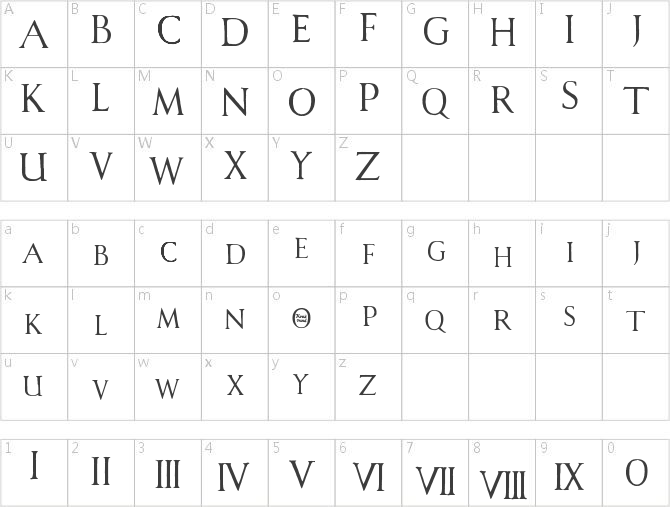
字體名稱: Antique
Antique Font by Marta van Eck
Antique Font by Marta van Eck字體字庫是一款讓人賞心悅目、百看不厭的英文字體,適合各類廣告和產品包裝設計應用,字體大小0.05MB,格式為ttf字體,上傳用戶是白刃寒走得慢,作者/版權方為未知